Webフォントのデザインテクニック04「字形を変更しよう」
Webフォントの中には、OpenType機能を使って字形を変更できるものがあります。
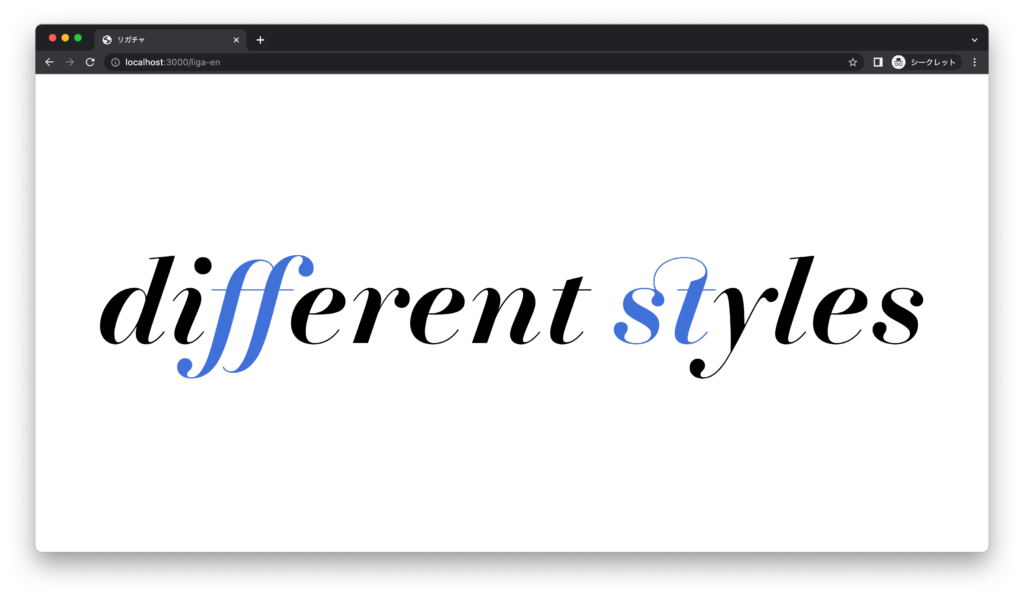
たとえば、濱明朝イタリックにはリガチャ liga と任意の合字 dlig が含まれています。これらは CSS で font-feature-settings を指定することで、利用を制御できます。
font-feature-settings: "liga" on, "dlig" on;
以下は liga と dlig をそれぞれ有効/無効にしたものを並べたものです。
通常、ブラウザのデフォルトでは liga は有効、dlig は無効になっています。
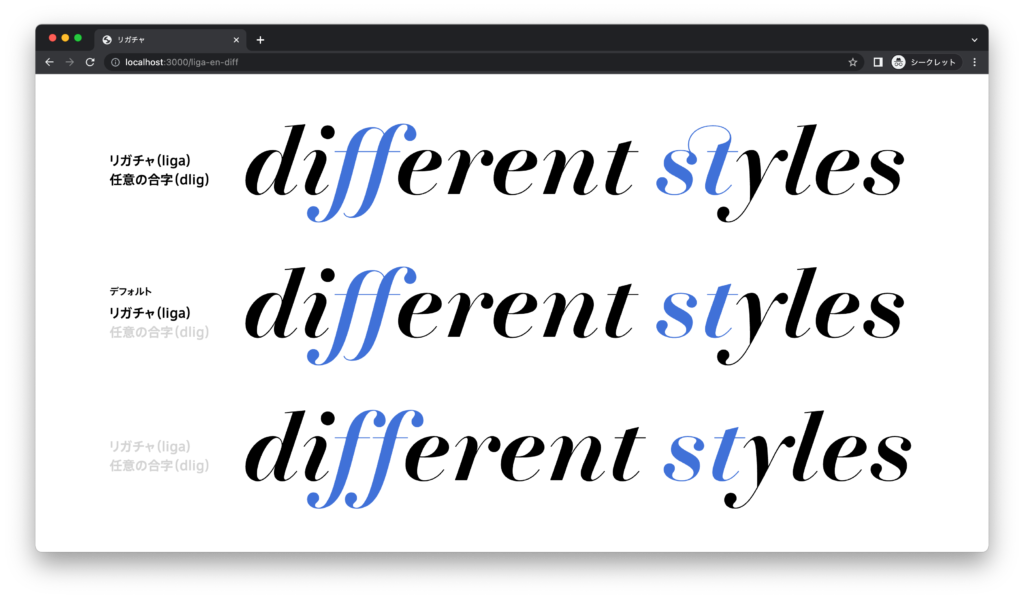
他にも、スモールキャップスや数字など、OpenType機能で利用できる字形があります。詳細については、以下のリソースが役立ちます。
今回は GSUB との対応がわかりやすいように font-feature-settings プロパティを用いましたが、実際は font-variant や、 font-variant-ligatures を用いる方が良いでしょう。詳しくは、以下のリソースを参照してください。
OpenType機能を利用する際には、いくつかの注意点があります。
フォントがOpenType機能を実装している必要があります。対応している機能を確認しましょう。
OSやブラウザによっては、OpenType機能に対応していない場合や意図しない表示になることがあります。対応状況を確認し、テストを行いましょう。
Webフォント配信サービスによっては、転送量削減などの理由でOpenType機能が省かれていたり、設定が必要な場合があります。利用の際には、サービスのドキュメントを参照しましょう。